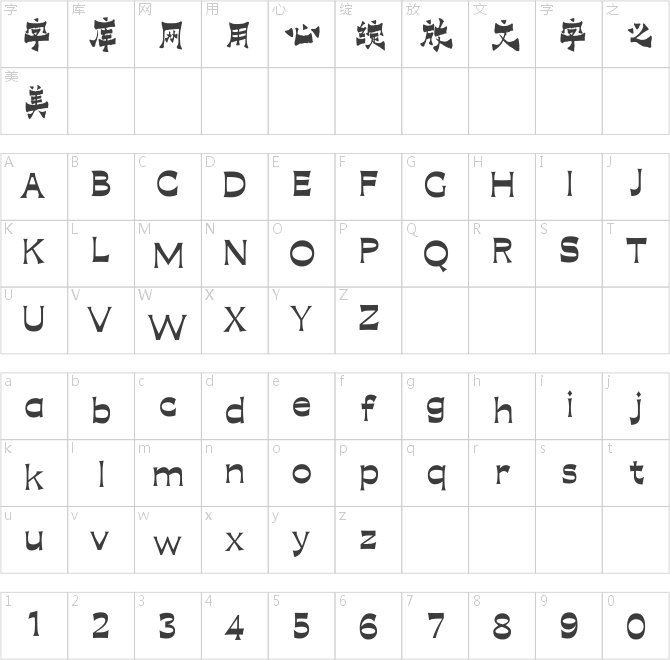
方正字跡-毛廣淞爨體,使用長鋒羊毫毛筆書寫,點畫成三角造型,靈動虛實相生;橫畫兩端上翹,成寬橫大勢,如千里陣云;撇、捺左右開張,運筆提頓極度夸張,收筆上揚,妙趣橫生;豎畫峻韌峭拔,力頂千鈞。樸厚中透著靈動,剛健與柔媚共有,金石與書卷同存。典雅蘊籍,醇厚遒勁,儀態萬方,極具廟堂壯美之景象。開創標題、榜書、匾額字體一代新風。
該字體風格是在立足魏晉書風基礎之上,結合現代審美情趣所創立的極為優秀的新字體。毛爨體深得“二爨"端樸方勁,雄強古拙之風骨,峻逸曠遠之神韻。運曠達胸襟于筆端,獨出機杼,高妙奇特,渾然天成,彰顯一派正大氣象。
作者毛廣淞,是中國書法家協會會員、中國書協書法培訓中心教授、中國國際友好聯絡會理事、清華大學書畫高研班導師、對外經貿大學研究生文化藝術導師。曾被評為“中國書法十大年度人物”。“毛廣淞爨體書法”受到國家版權局版權登記保護。收起